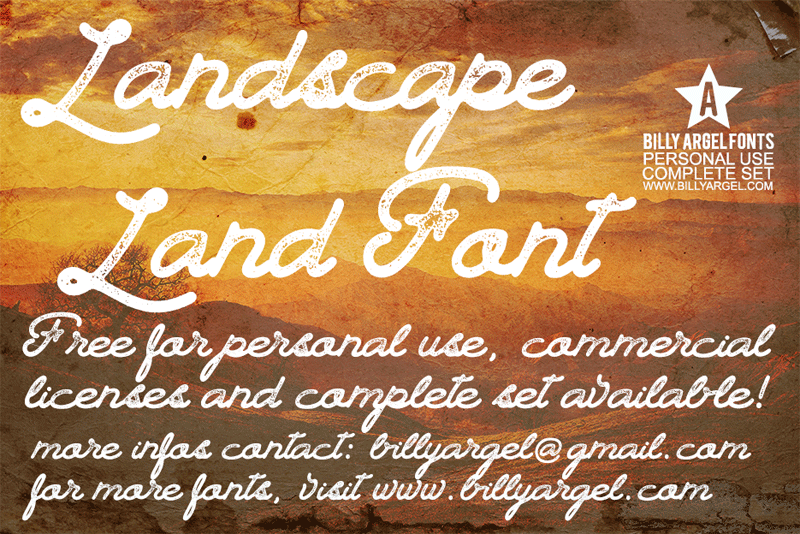
Landscape Land Font – Download Grátis
A Landscape Land Font é uma tipografia typewriter que traz à tona o charme dos anos 70 com seus traços elegantes e detalhes únicos. Desenvolvida pelo designer Hamilton, esta fonte oferece um tom distinto para qualquer projeto de escrita manuscrita ou digital, tornando-a perfeita para criações memoráveis e memoráveis. Em termos de uso pessoal, a Landscape Land Font é disponível gratuitamente, mas as licenças comerciais e o conjunto completo estão disponíveis em sua página oficial, onde você pode encontrar mais informações úteis sobre como adquirir o produto desejado. Acesse www.billyargel.com para obter um contato direto com o designer e explore ainda mais as possibilidades criativas desta fonte typewriter única e reconhecível.